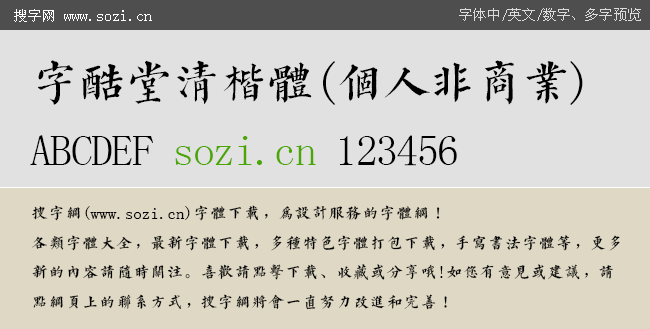
字酷堂清楷體(個(gè)人非商業(yè))
搜字網(wǎng)提供一款字酷堂清楷體(個(gè)人非商業(yè))中文書(shū)法字體下載,字酷堂清楷體是一款非常漂亮的手寫(xiě)風(fēng)格書(shū)法字體,字體端正大方,整體效果非常漂亮,適合應(yīng)用于廣告設(shè)計(jì)、名片設(shè)計(jì)、包裝印刷、海報(bào)設(shè)計(jì)等應(yīng)用。